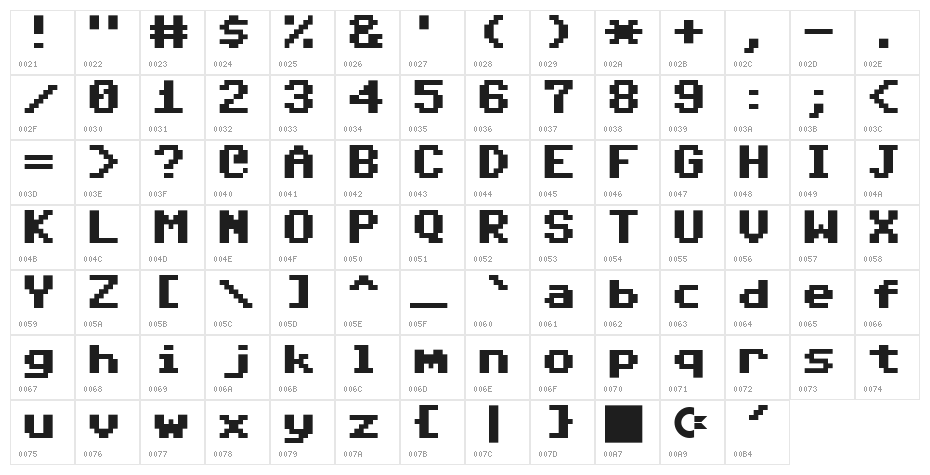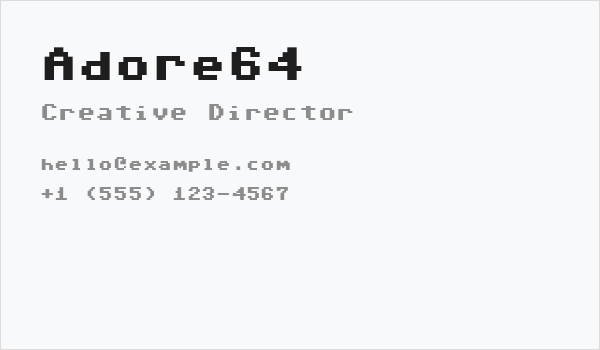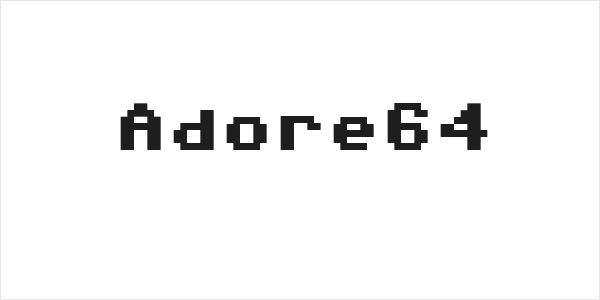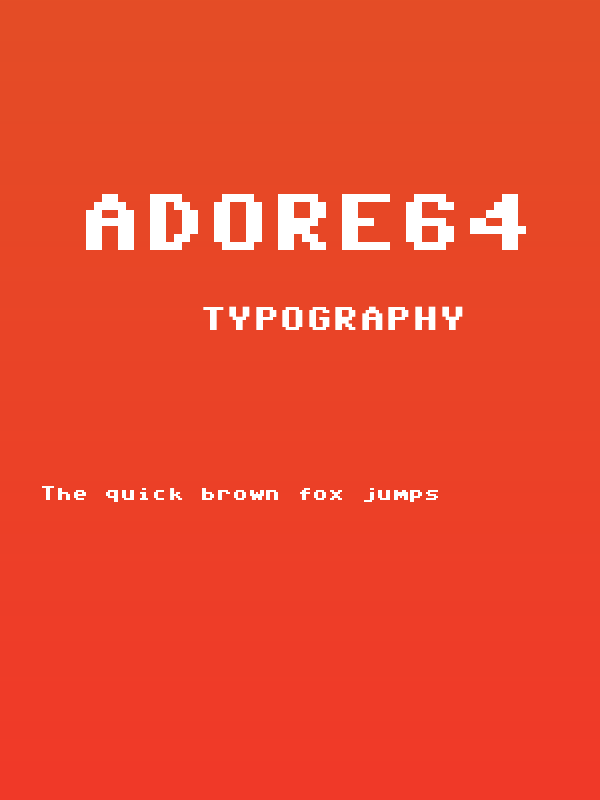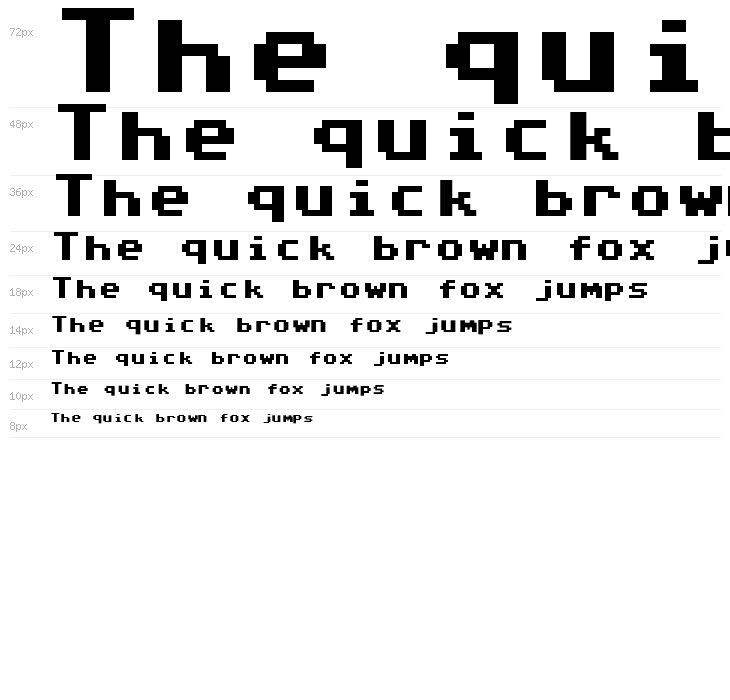
Adore64 Font
| Caso d'uso | Logos, Digital displays, Retro-themed designs |
| Progetti proposti | Ideal for retro video game designs, digital art projects, and any creative work that seeks to evoke nostalgia for early computing and gaming eras. |